Meier, Hans Eduard
Hans Eduard Meier war ein Schweizer Schriftgestalter, Typograf und Grafikdesigner. Geboren am 30. Dezember 1922 in Horgen bei Zürich. Gestorben am 15. Juli 2014 in Obstalden am Walensee in der Schweiz.
Bekannt wurde Hans Eduard Meier durch seine Schriftfamilie »Syntax«, einer Jüngeren Grotesk (Humanist), deren Majuskeln, insbesondere in fetten Schriftstilvarianten, an die Typometrie einer altgriechischen Lapidarschrift erinnern. Die Protoentwürfe entstanden Mitte der 1950er Jahre. Die ersten Schriftstile der serifenlosen Syntax erschienen 1968 als Bleisatzschrift bei der D. Stempel AG in Frankfurt a.M. (infolge Linotype, ab 2006 Monotype). Heute wird diese Schrift als Schriftsippe in der »Linotype Library« (Monotype GmbH) vertrieben. Seit dem Jahr 2000 liegt diese Schriftgroßfamilie komplett als Schriftsystem in rund hundert Schriftstilvarianten vor, u.a. als »Syntax Next«, »Syntax Letter«, »Syntax Serif« und »Syntax Lapidar«.
Weitere Druckschriften von Hans Eduard Meier sind die ABC Schrift Eins bis Drei (Elsner+Flake), ABC Vario Eins bis Drei (Elsner+Flake), Barbedor ® (Linotype Library ®), die ITC Syndor ® (ITC Library ®), die Elysa (Elsner+Flake) und die Oberon (Elsner+Flake), die 1994 als Hausschrift für das Institut für Computersysteme der Eidgenössischen Technischen Hochschule Zürich (ETH) entworfen wurde.
Biografie
1939–1942 | Nach Beendigung der Primar- und Sekundarschule absolviert Hans Eduard Meier in Horgen am Zürichsee eine Ausbildung zum Handschriftsetzer.
1943 | Besuch der Fachklassen für Setzer und Typografie an der Kunstgewerbeschule Zürich (heute ZHdK Zürcher Hochschule der Künste).
1946–1948 | Nach dem Abschluss der Kunstgewerbeschule freiberufliche Tätigkeit als Werbegrafiker für Industrie, Verlage und Kulturevents, u.a. für die Schweizer Kulturzeitschrift »DU«.
1949 | Ab dem Wintersemester 1949/1950 bis 1986 unterrichtete Hans Eduard Meier Schrift, Typografie und konstruktives Zeichnen an der Kunstgewerbeschule Zürich.
1950 | Ab Mitte der 1950er Jahre entstehen die ersten Entwürfe für die Drucktype Syntax.
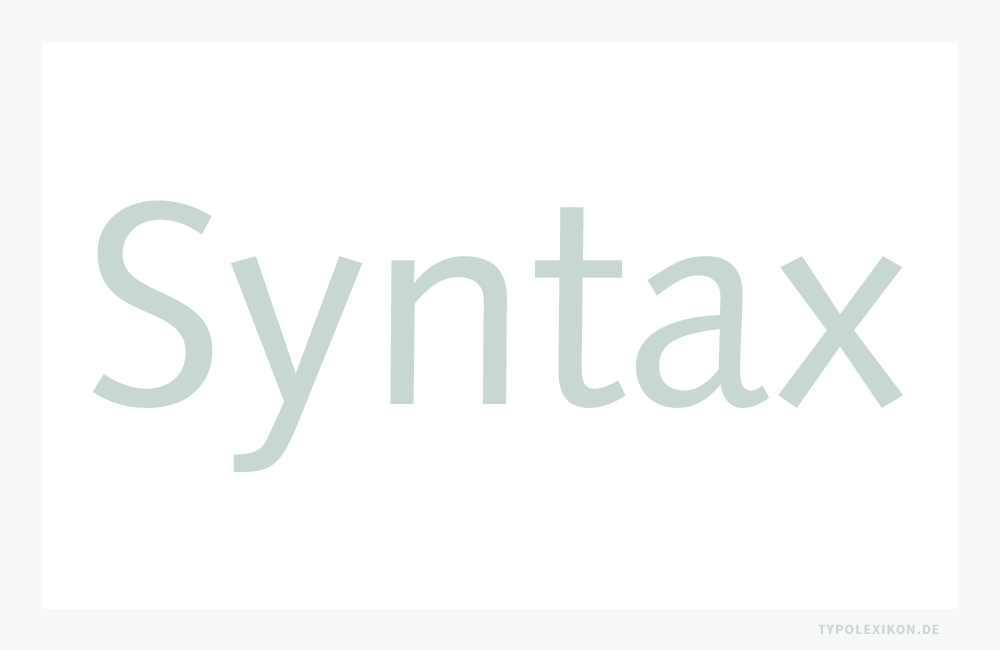
1978 | Vortragsreise nach Providence, Portland, Los Angeles und San Francisco sowie 1991 nach Boston und Montreal.
1984 | Freie Tätigkeit im Segment Electronic Publishing am Institut für Informatik der Eidgenössischen Technischen Hochschule Zürich (ETH). 1)
1986 | Pensionierung nach seiner Tätigkeit als Fachlehrer für Schrift und Zeichnen an der Kunstgewerbeschule Zürich.
2014 | Hans Eduard Meier stirbt am 15. Juli 2014 im Alter von 92 Jahren in Obstalden am Walensee in der Schweiz. 2)
Schriften von Hans Eduard Meier (1955–2013)
- ABC Schrift Eins Regular, 2003, Elsner+Flake
ABC Schrift Eins Italic, 2003, Elsner+Flake
ABC Schrift Eins Regular OSF, 2003, Elsner+Flake
ABC Schrift Eins Italic OSF, 2003, Elsner+Flake
ABC Schrift Zwei Regular, 2003, Elsner+Flake
ABC Schrift Zwei Italic, 2003, Elsner+Flake
ABC Schrift Zwei Regular OSF, 2003, Elsner+Flake
ABC Schrift Zwei Italic OSF, 2003, Elsner+Flake
ABC Schrift Drei Regular, 2003, Elsner+Flake
ABC Schrift Drei Italic, 2003, Elsner+Flake
ABC Schrift Drei Regular OSF, 2003, Elsner+Flake
ABC Schrift Drei Italic OSF, 2003, Elsner+Flake
ABC Vario Eins Regular, Elsner+Flake
ABC Vario Eins Italic, Elsner+Flake
ABC Vario Eins Regular OSF, Elsner+Flake
ABC Vario Eins Italic OSF, Elsner+Flake
ABC Vario Zwei Regular, Elsner+Flake
ABC Vario Zwei Italic, Elsner+Flake
ABC Vario Zwei Regular OSF, Elsner+Flake
ABC Vario Zwei Italic OSF, Elsner+Flake
ABC Vario Drei Regular, Elsner+Flake
ABC Vario Drei Italic, Elsner+Flake
ABC Vario Drei Regular OSF, Elsner+Flake
ABC Vario Drei Italic OSF, Elsner+Flake - Barbedor Bold, 1990, Linotype Library
Barbedor Bold Italic, 1990, Linotype Library
Barbedor Heavy, 1990, Linotype Library
Barbedor Heavy Italic, 1990, Linotype Library
Barbedor Medium, 1990, Linotype Library
Barbedor Medium Italic, 1990 Linotype Library
Barbedor Regular, 1990, Linotype Library
Barbedor Regular Caps, 1990, Linotype Library - Elysa Bold, 1994, 2000, Elsner+Flake
Elysa Book, 1994, 2000, Elsner+Flake<
Elysa Italic, 1994, 2000, Elsner+Flake
Elysa Small Caps, 1994, 2000, Elsner+Flake - Gesta Antiqua, 2004, Elsner+Flake
- ITC Syndor Bold, 1992, ITC Library
ITC Syndor Bold OsF, 1992, ITC Library
ITC Syndor Bold Italic, 1992, ITC Library
ITC Syndor Bold Italic OsF, 1992, ITC Library
ITC Syndor Book, 1992, ITC Library
ITC Syndor Book SC, 1992, ITC Library
ITC Syndor Book OsF, 1992, ITC Library
ITC Syndor Book Italic, 1992, ITC Library
ITC Syndor Book Italic OsF, 1992, ITC Library
ITC Syndor Medium, 1992, ITC Library
ITC Syndor Medium SC, 1992, ITC Library
ITC Syndor Medium OsF, 1992, ITC Library
ITC Syndor Medium Italic, 1992, ITC Library
ITC Syndor Medium Italic OsF, 1992, ITC Library - Linotype Syntax Lapidar Display, Linotype Library
Linotype Syntax Lapidar Serif Display, Linotype Library
Linotype Syntax Lapidar Serif Text, Linotype Library
Linotype Syntax Lapidar Text, Linotype Library
Linotype Syntax Letter, Linotype Library
Linotype Syntax Letter Labidar, Linotype Library
Linotype Syntax Next, Linotype Library
Linotype Syntax Serif, Linotype Library - Meier Kapitalis, 2012, Elsner+Flake
- Oberon, 1994, Elsner+Flake
- Parnassia, 2012, Parnassia Vättis
- SNB-Alphabet, 1994